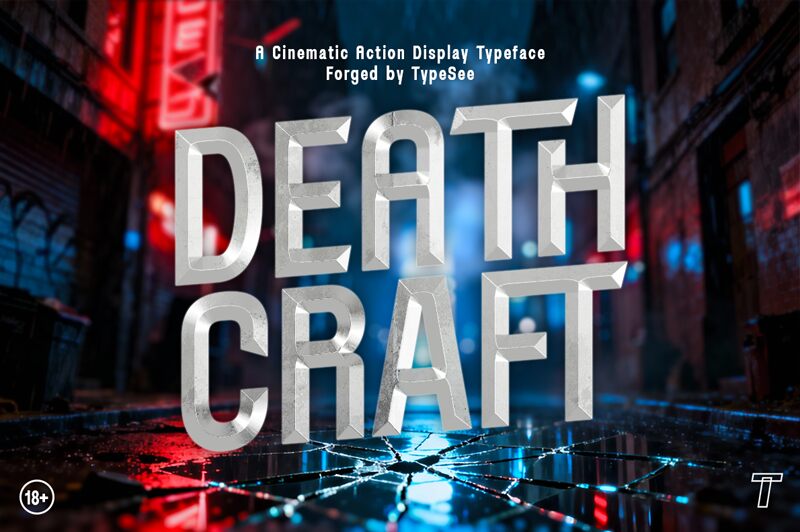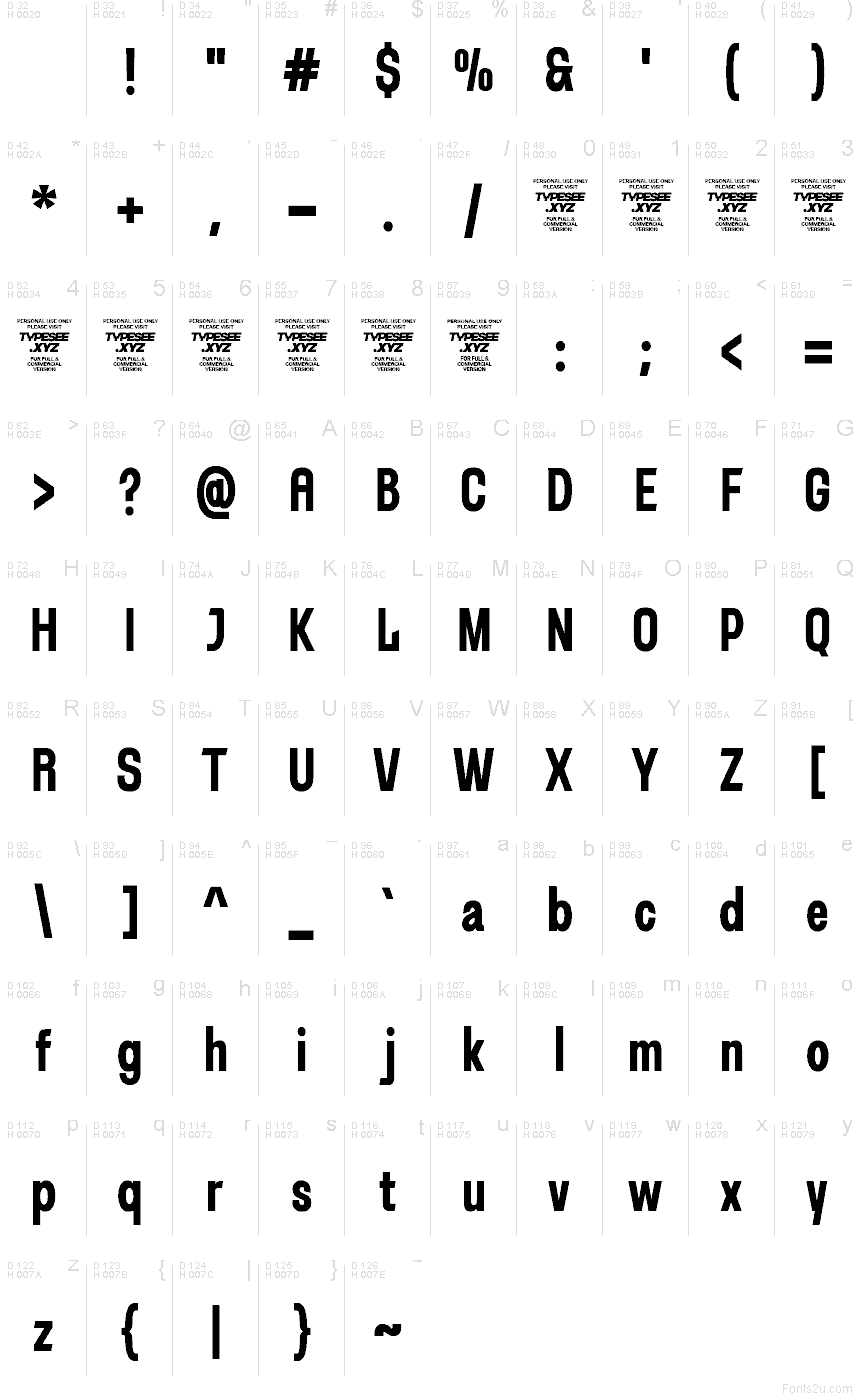
Death Craft
Death Craft von Typesee Type Foundry ist eine kostenlose, wuchtige serifenlose Schrift mit einer markanten, plakativen Anmutung. Die Buchstaben wirken eng gesetzt und massiv, mit abgerundeten Verbindungen und reduzierten Formen, die dem Schriftbild eine direkte, düstere und fast industrielle Note verleihen, statt auf Eleganz zu setzen.
Diese kostenlose Schriftart eignet sich perfekt für Musik-Flyer, Horror-Titel, Streetwear-Designs, Splash-Screens in Games und auffällige Verpackungen – überall dort, wo ein kompakter Schriftblock mehr als nur Dekoration sein soll. Sie funktioniert auch hervorragend für kurze Headlines oder Titelkarten, da die dicken Kleinbuchstaben und hohen Striche selbst kurze Sätze kompakt und hart wirken lassen.